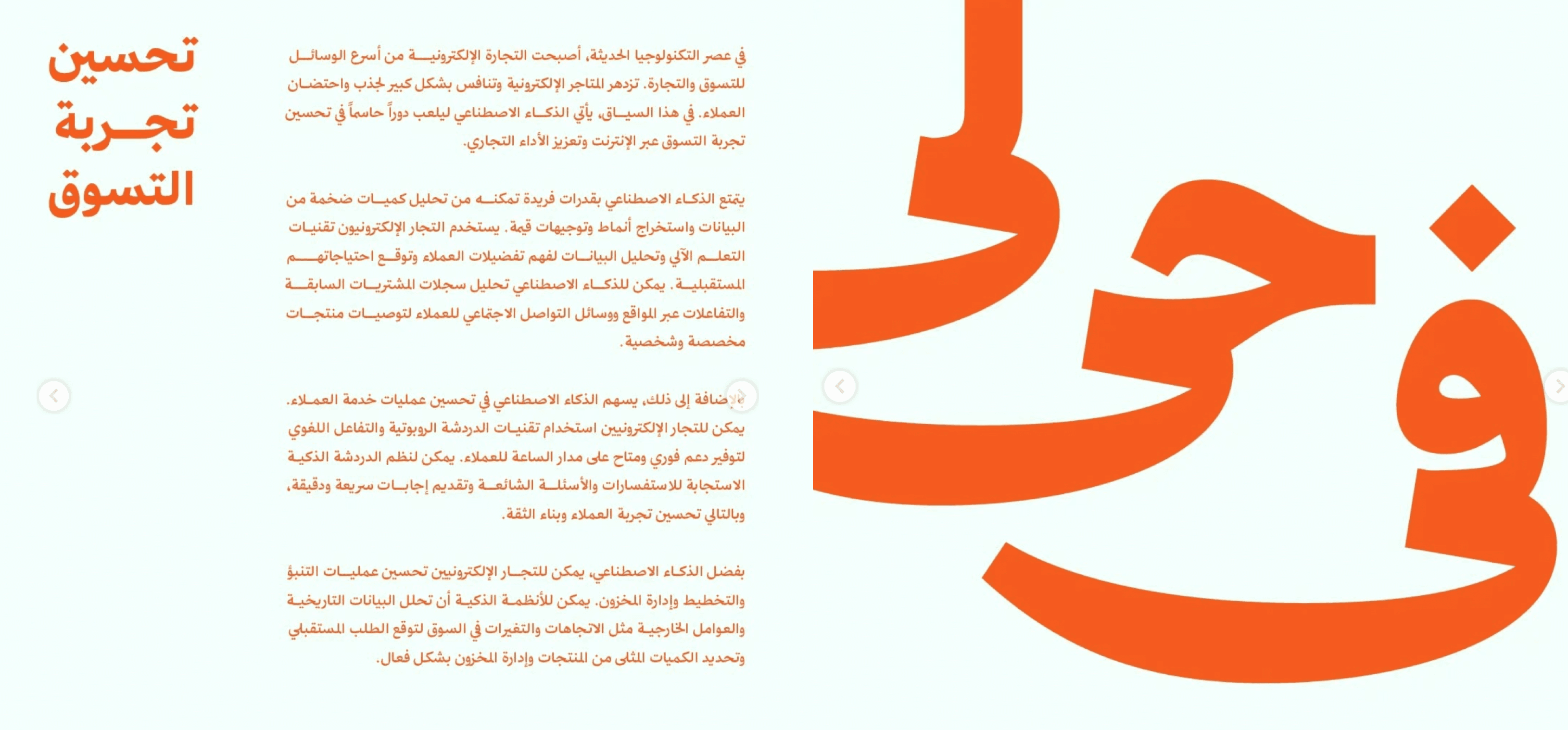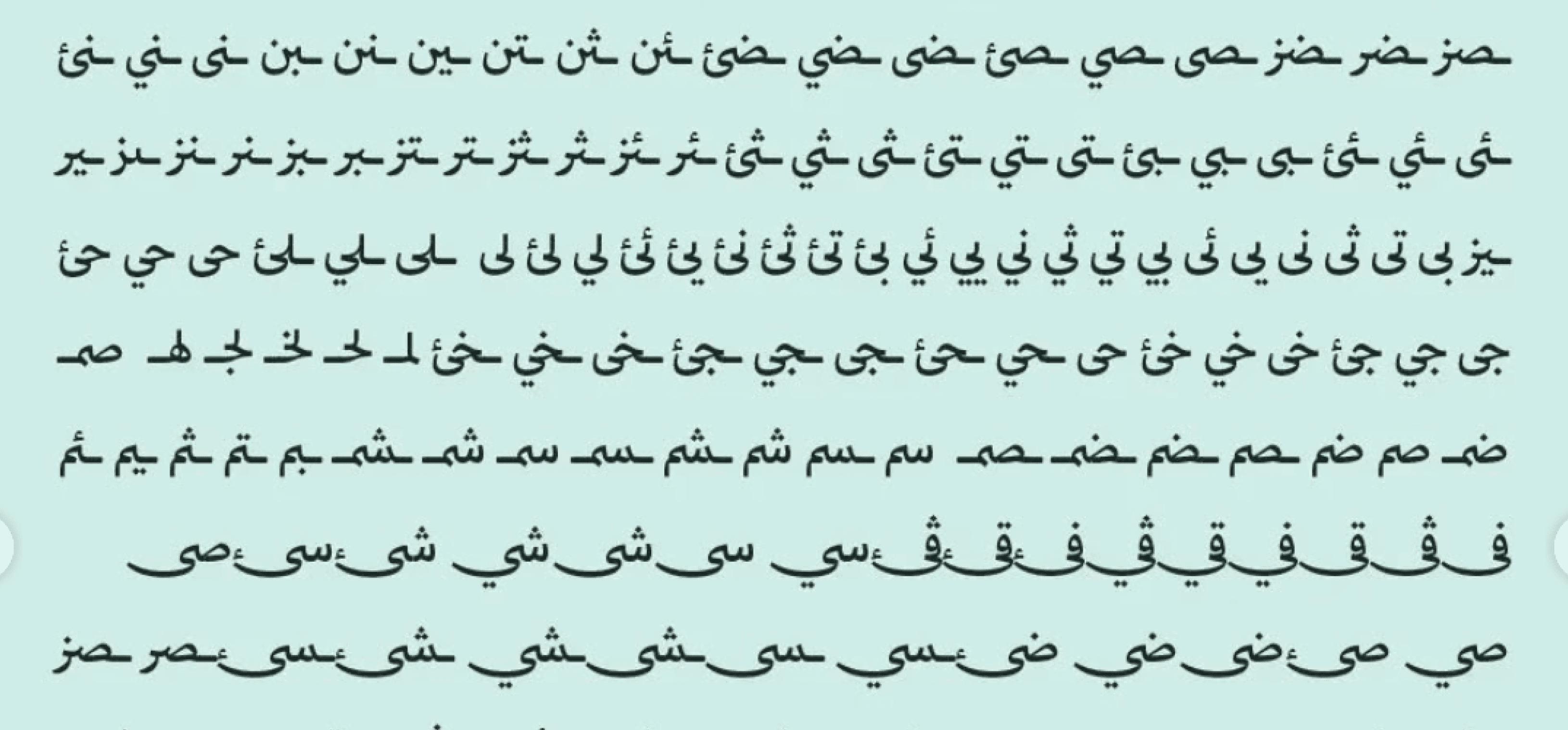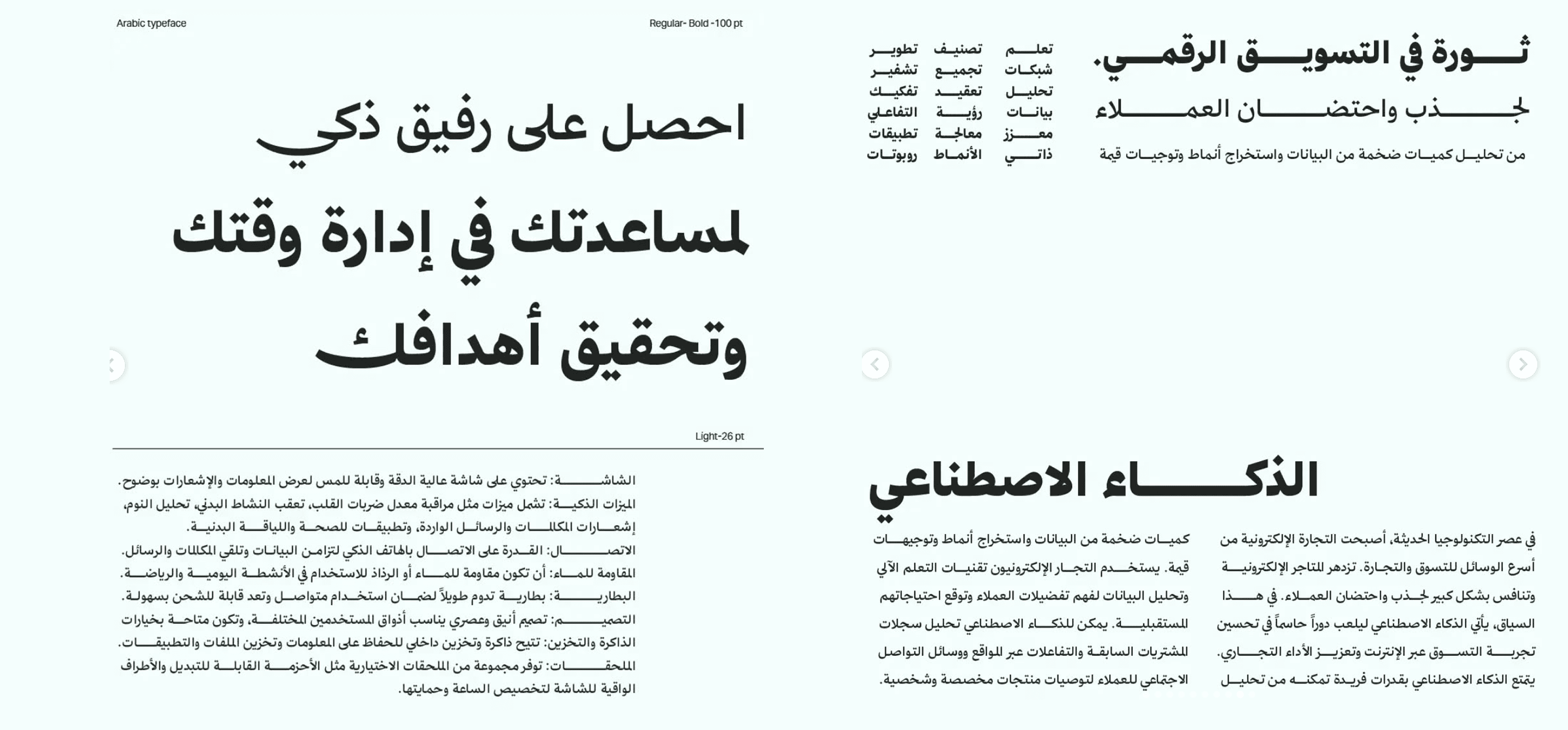
خط عربي بطابع طباعي حديث، مستوحى من أسلوب النسخ التقليدي لكن بتصميم عصري واضح الخطوط.
يتميز بتوازن بصري وأناقة هندسية، مما يجعله مثاليًا لتصميم الشعارات، الهوية البصرية، والعناوين المطبوعة والرقمية.